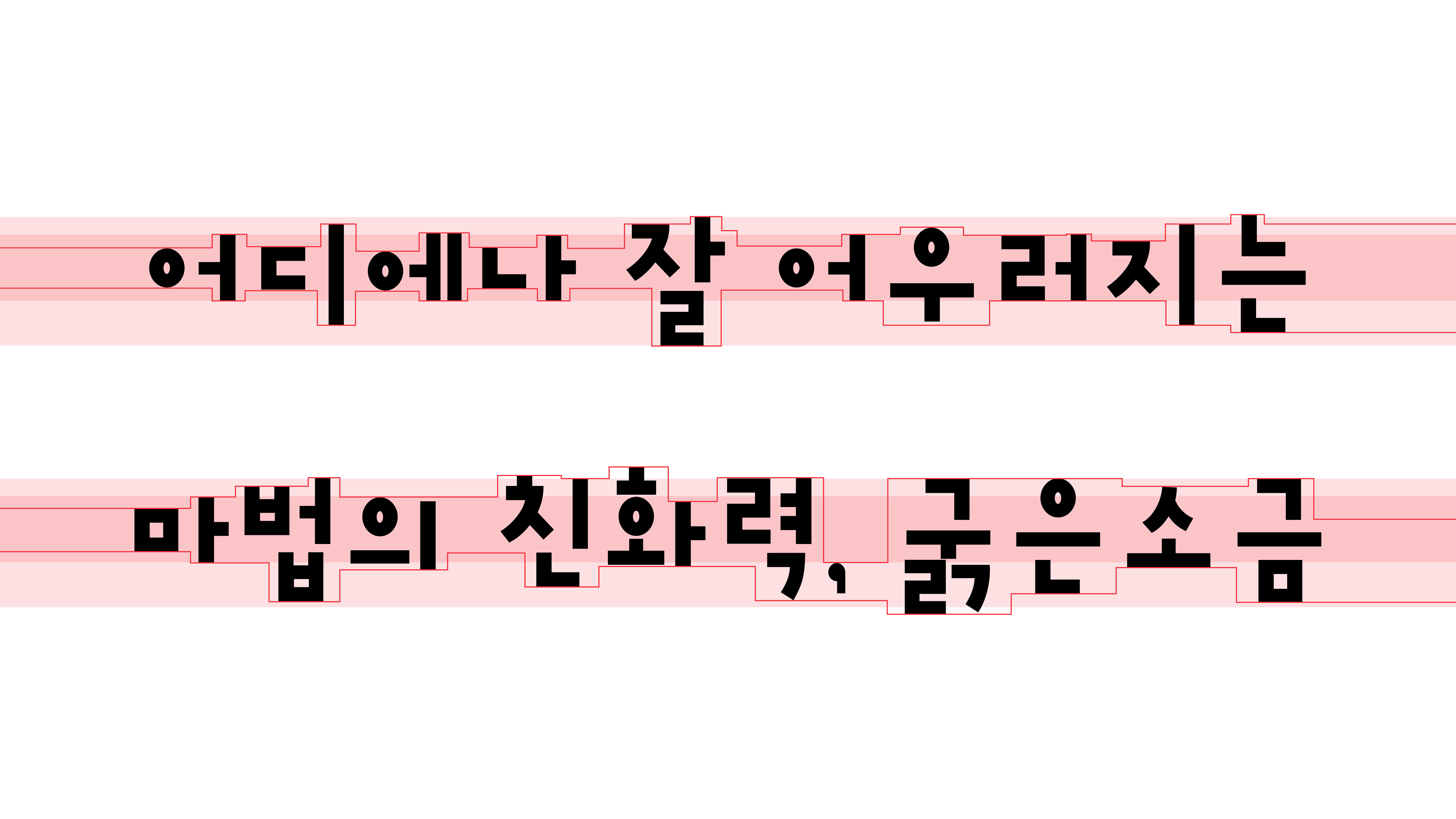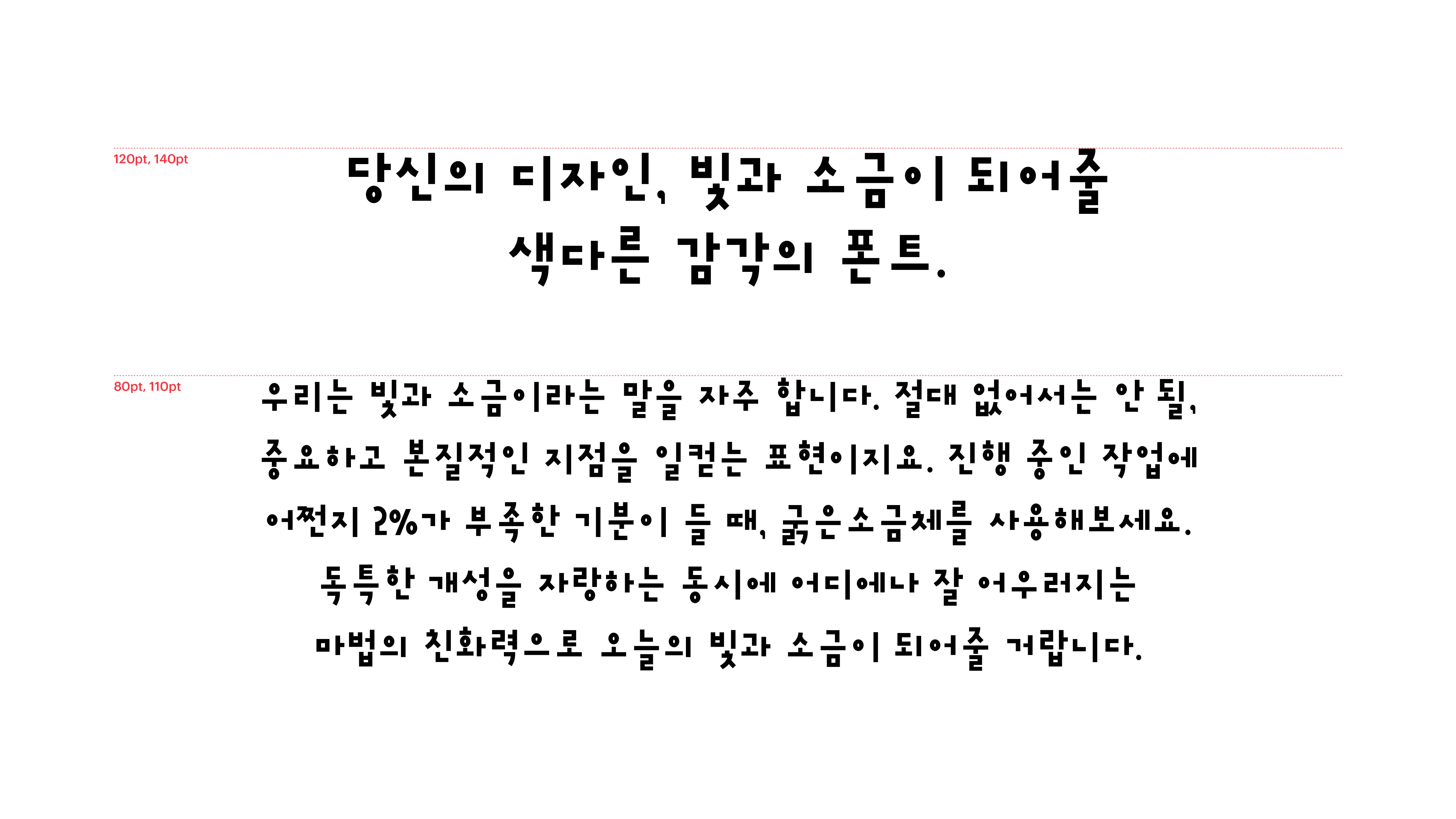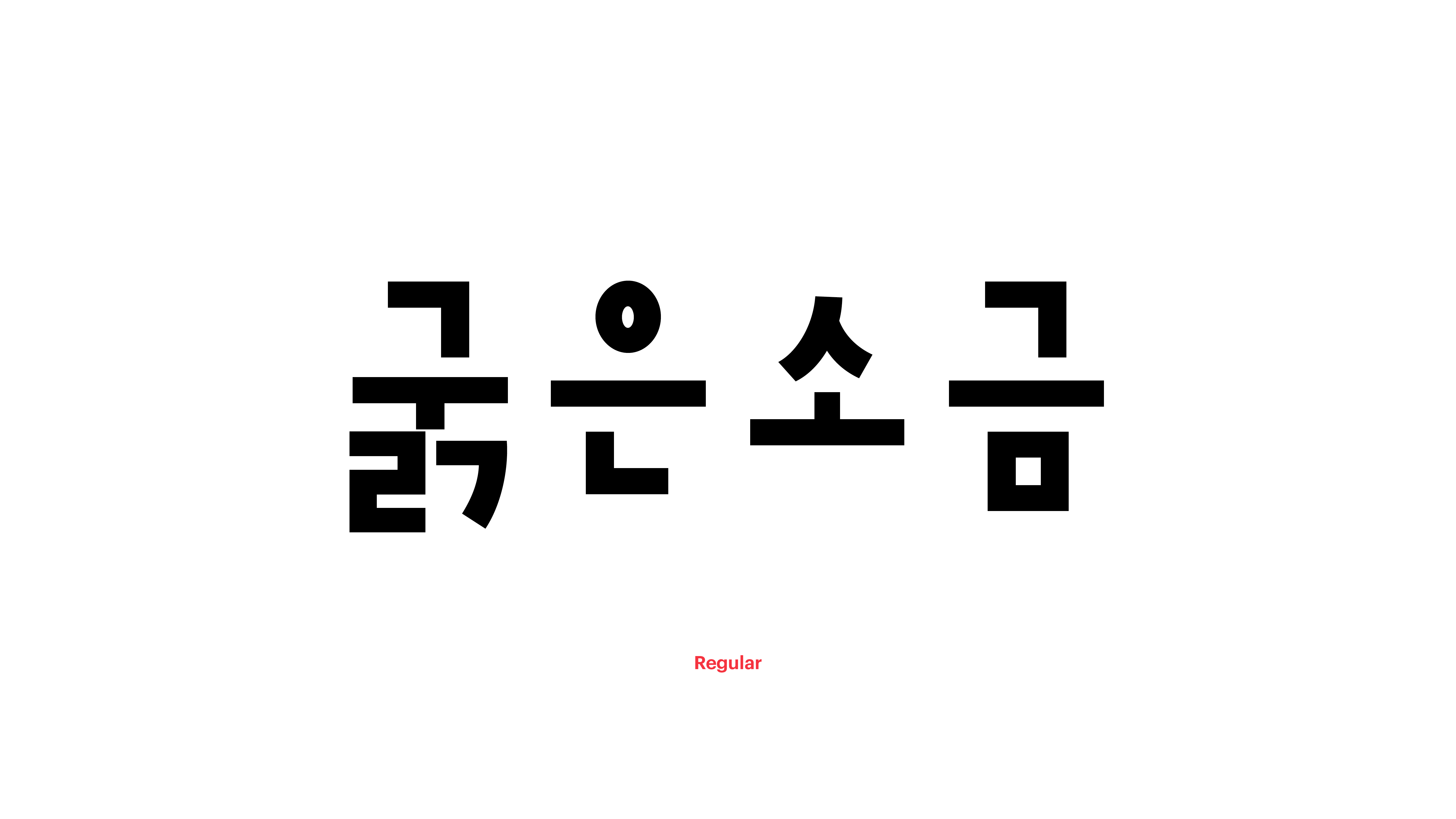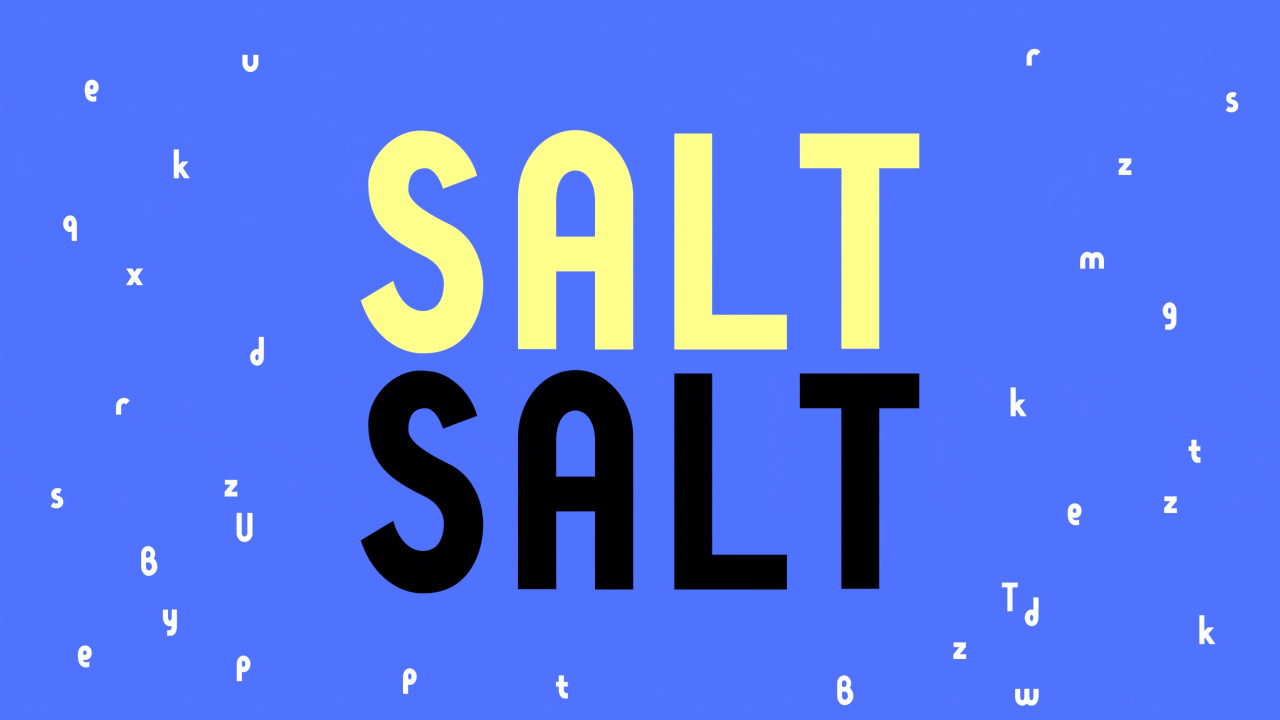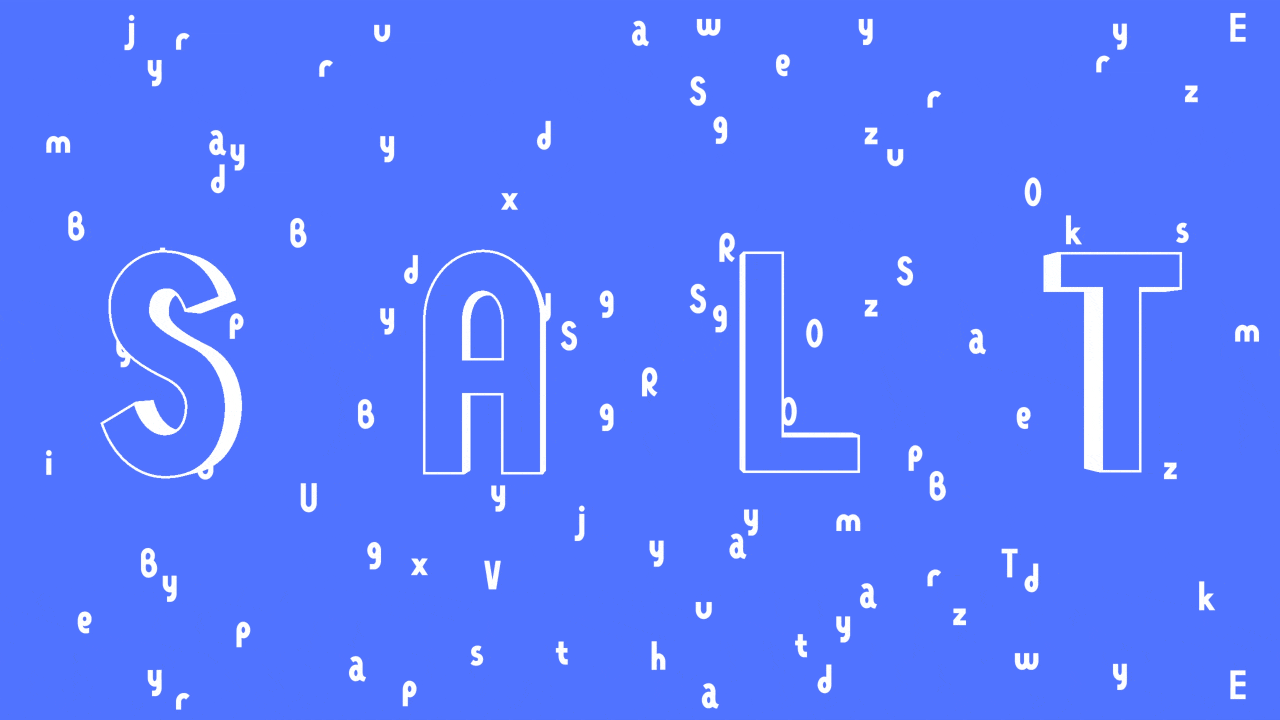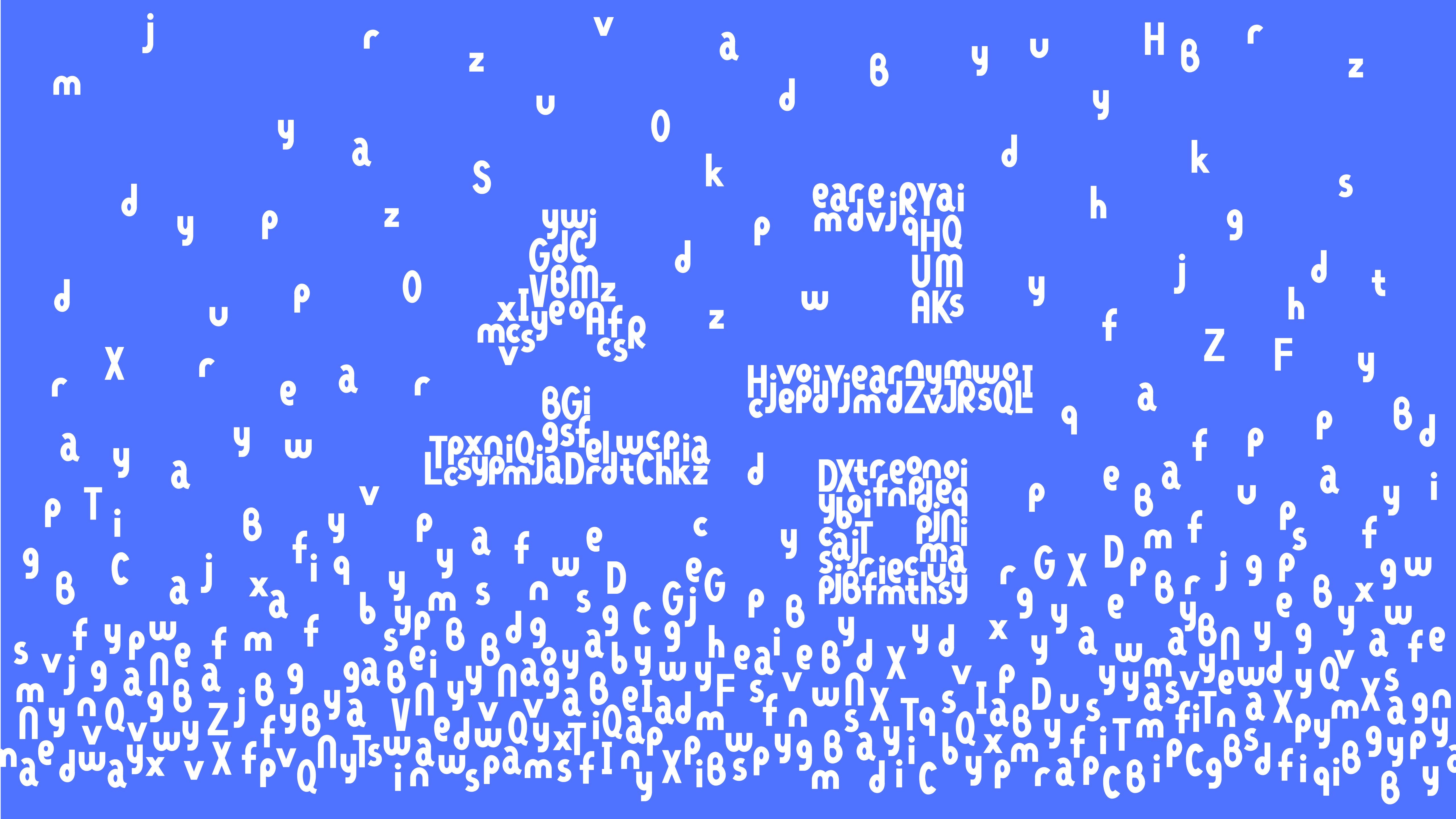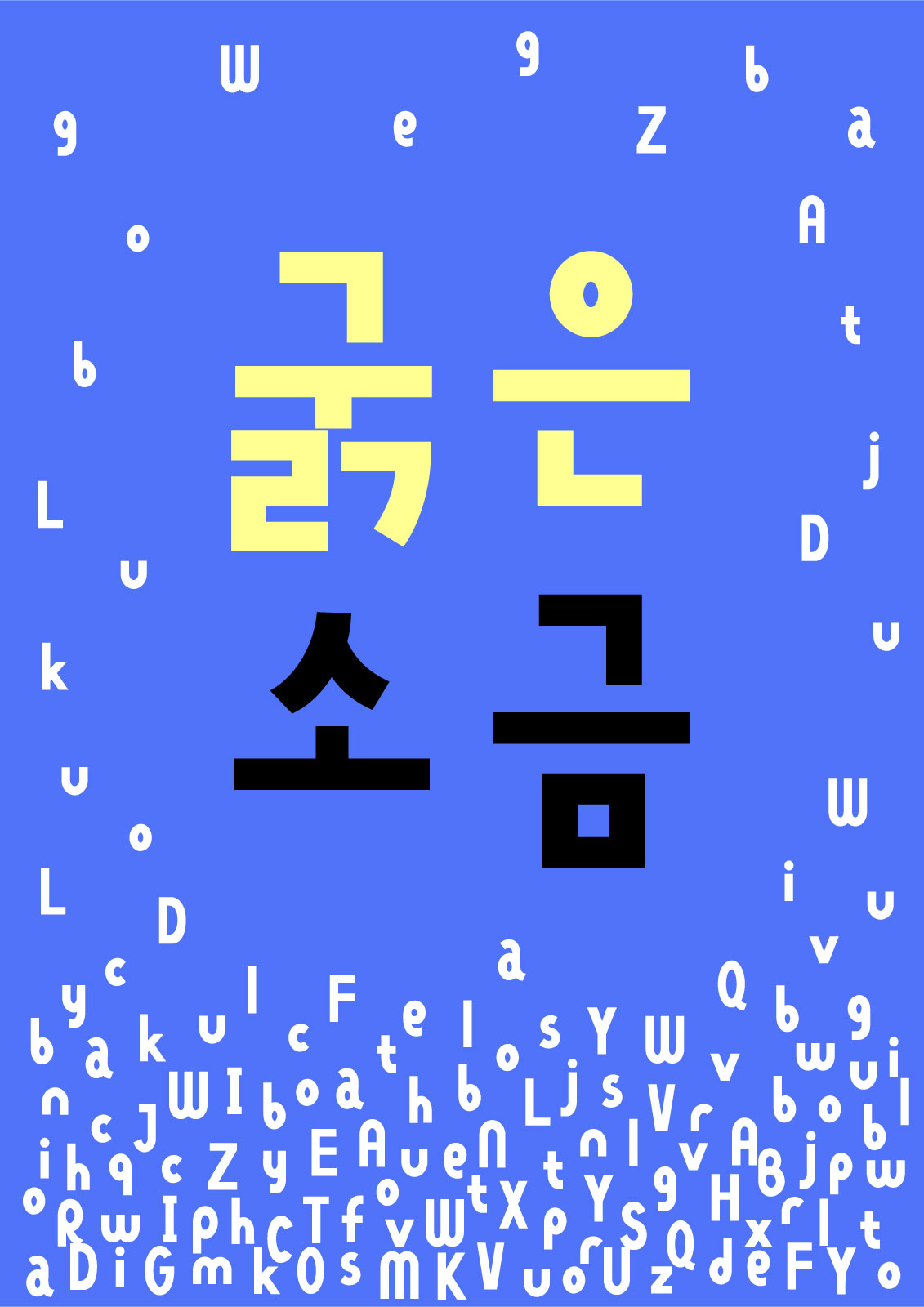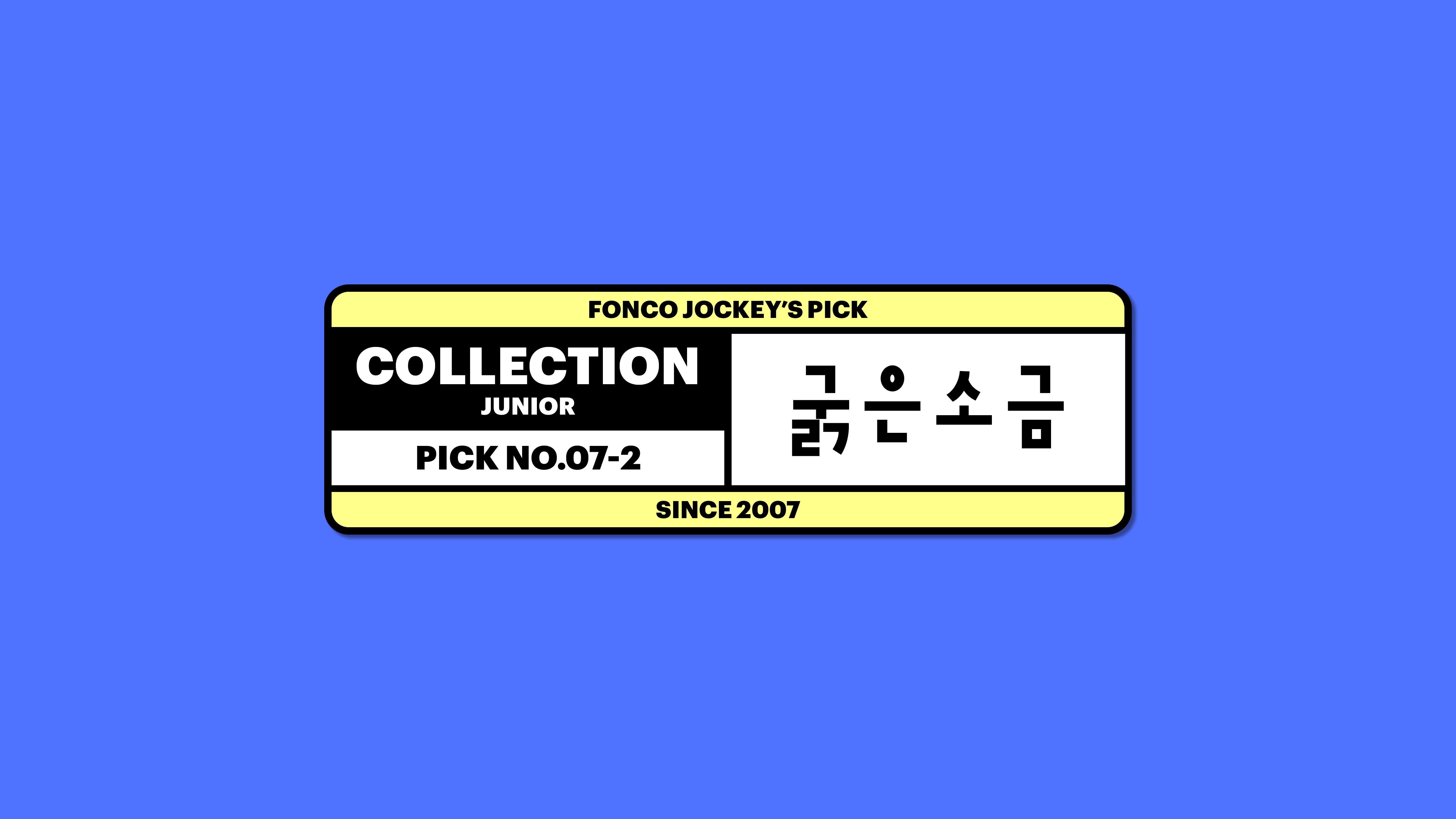
굵은소금
Yoon 굵은소금
우리는 빛과 소금이라는 말을 자주 합니다. 절대 없어서는 안 될, 중요하고 본질적인 지점을 일컫는 표현이지요. 진행 중인 작업에 어쩐지 2%가 부족한 기분이 들 때, 굵은소금체를 사용해보세요. 독특한 개성을 자랑하는 동시에 어디에나 잘 어우러지는 마법의 친화력으로 오늘의 빛과 소금이 되어줄 거랍니다.